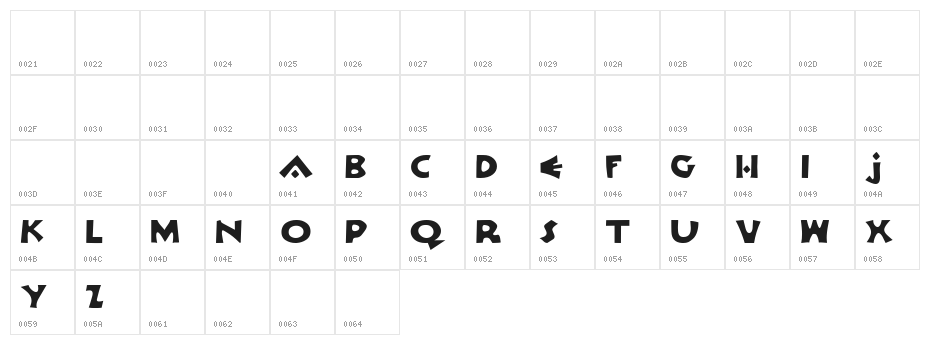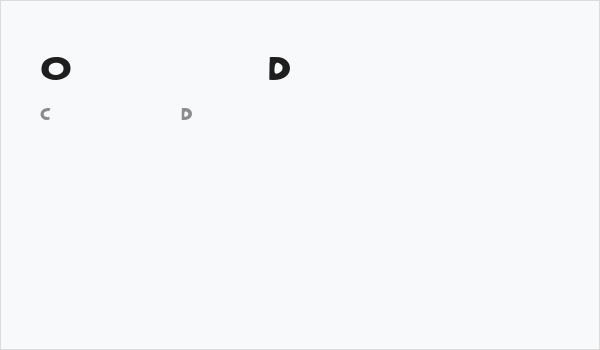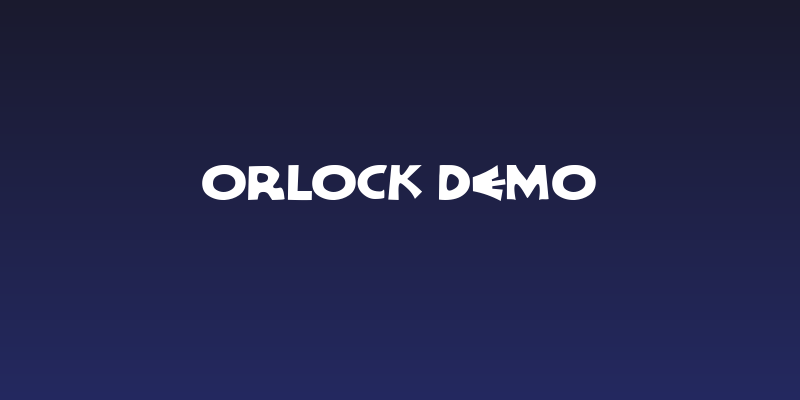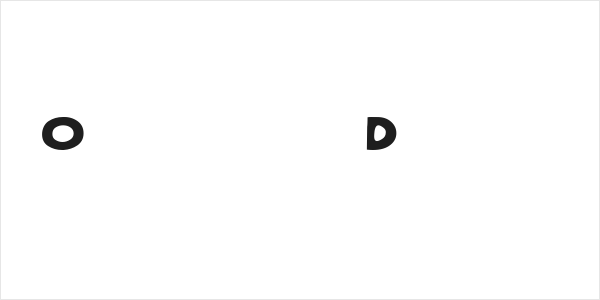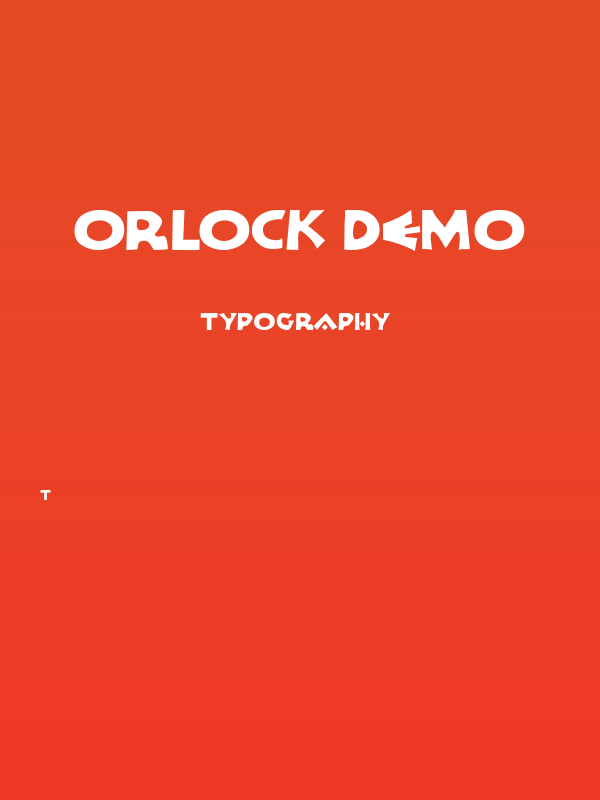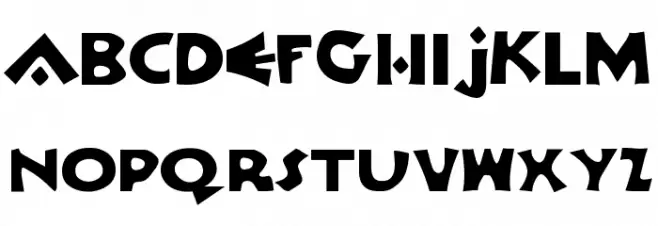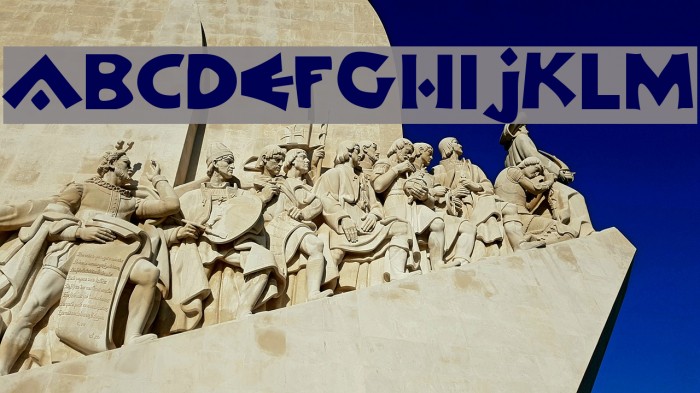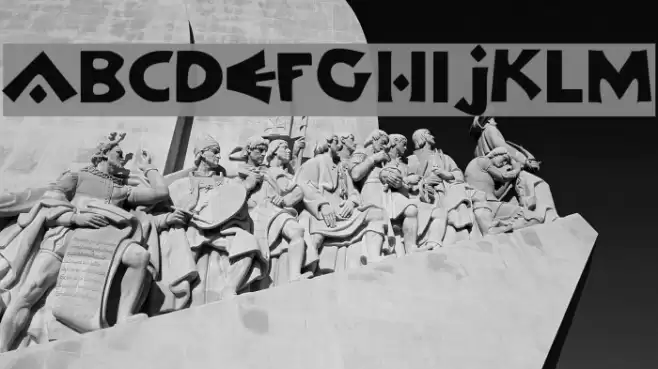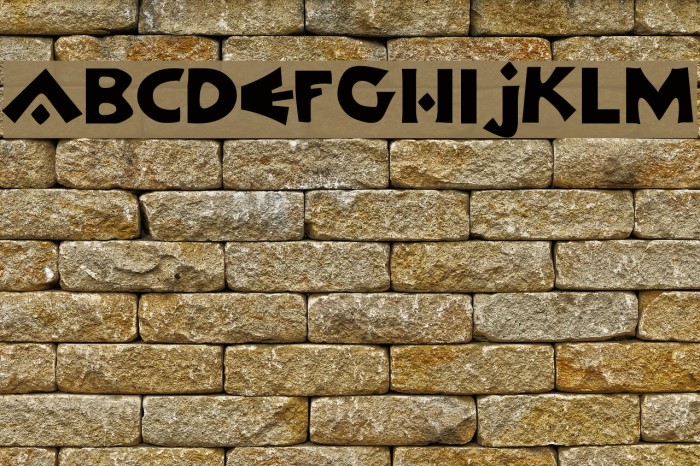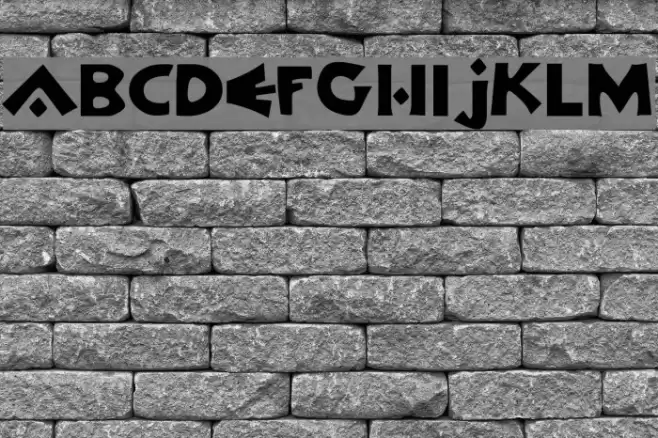
Orlock Demo Font
| Vorgeschlagene Projekte | Ideal for posters, logos, video game graphics, and any project requiring a bold, eye-catching typeface. |